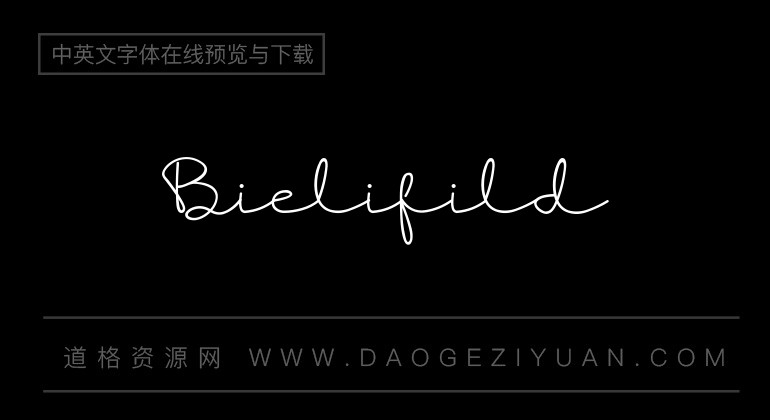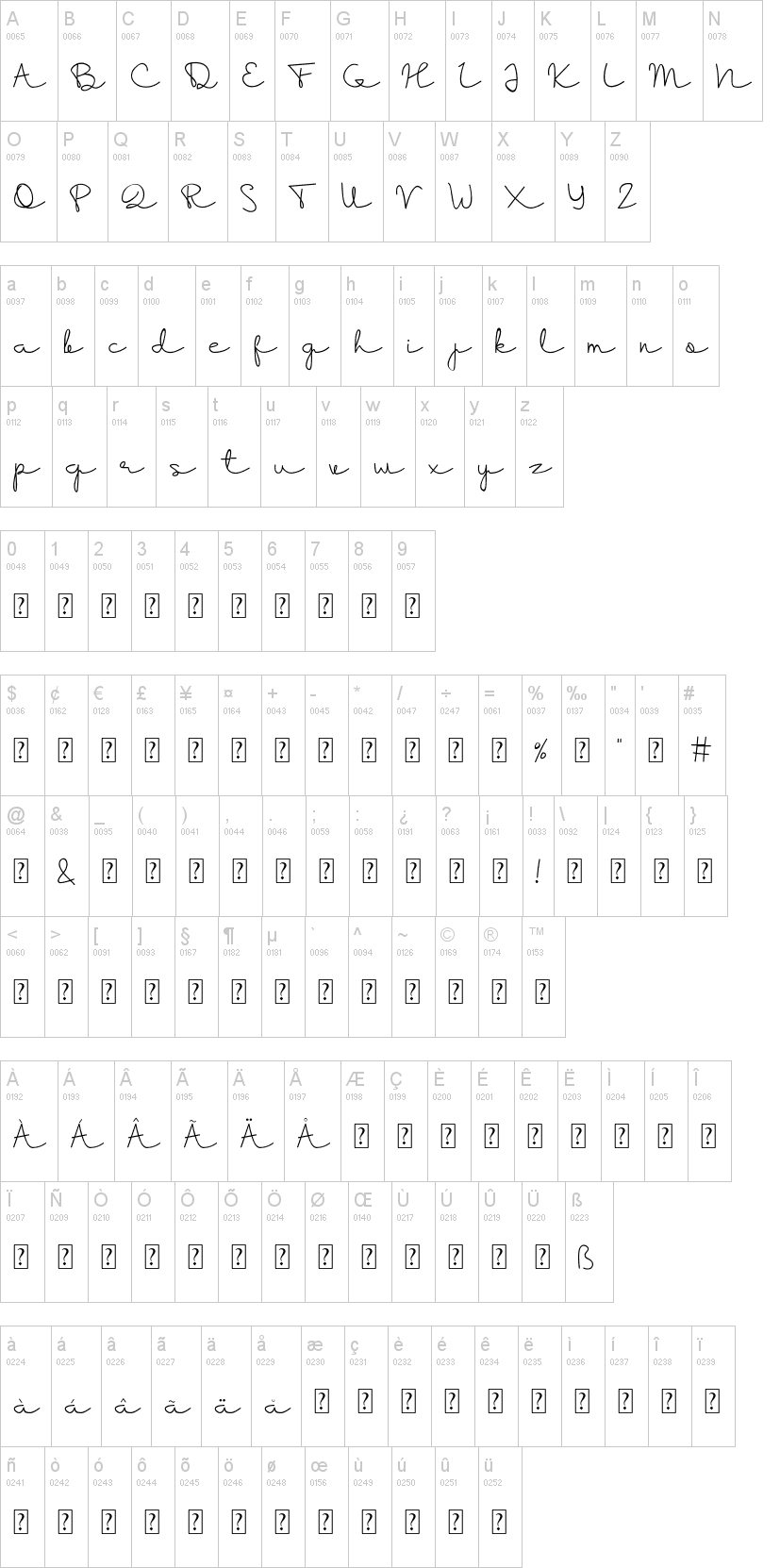
Bielifild 是一种比利时式的字体,它由荷兰设计师Jos Buivenga于2008年设计。这种字体采用比利时风格的基本元素,如圆角、粗细、长短等,结合现代设计来创造出独特的字体风格。它具有细腻而柔和的线条,可以带来温暖、舒适的感觉,适合用于品牌标识、封面、广告等。内容介绍
Bielifild是一款非常不错的手写艺术字体,具有很好的视觉感,适合于文化类的宣传设计、商业类品牌的广告和产品包装设计以及个性化文字排版等较多场景。